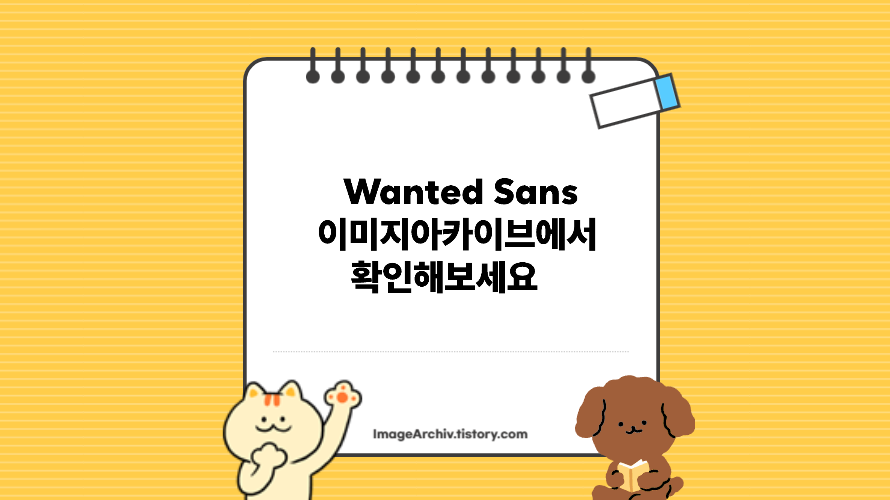
Wanted Sans
Wanted Sans는 원티드랩의 브랜드 아이덴티티를 효과적으로 전달하기 위해 개발된 서체입니다. '일하는 사람들의 모든 가능성'이라는 원티드의 정신을 시각적으로 표현하고자, 기하학적인 형태를 기반으로 한 산세리프 글꼴로 제작되었습니다. 이 서체는 제목과 본문 모두에서 자연스럽게 사용될 수 있도록 설계되어, 원티드의 목소리를 일관되게 전달합니다.
형태적 특징
Wanted Sans는 기하학적인 구조를 바탕으로 하여, 직선과 곡선이 조화를 이루는 디자인을 특징으로 합니다. 이러한 형태는 깔끔하고 현대적인 인상을 주며, 다양한 굵기 옵션을 통해 제목, 본문, 캡션 등 다양한 용도로 활용이 가능합니다. 또한, 가독성을 고려한 설계로, 긴 텍스트에서도 편안한 독서를 지원합니다.
활용 분야
Wanted Sans는 원티드랩의 공식 문서, 홍보물, 웹사이트 등에서 활용되며, 교육 자료, 아동 도서, 블로그 등에서도 활용할 수 있습니다. 다양한 굵기 옵션을 통해 제목, 본문, 캡션 등 다양한 용도로 활용이 가능합니다.